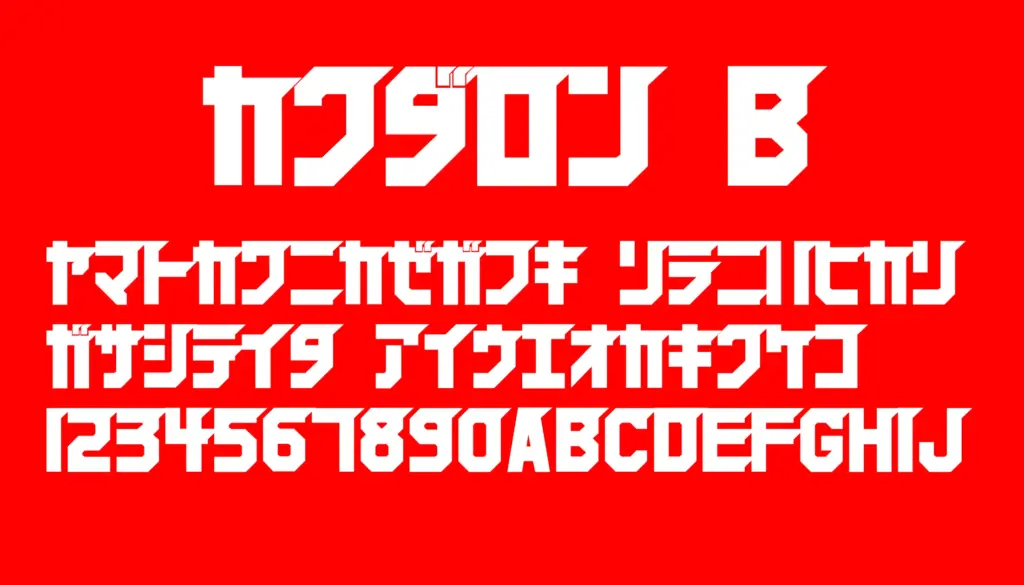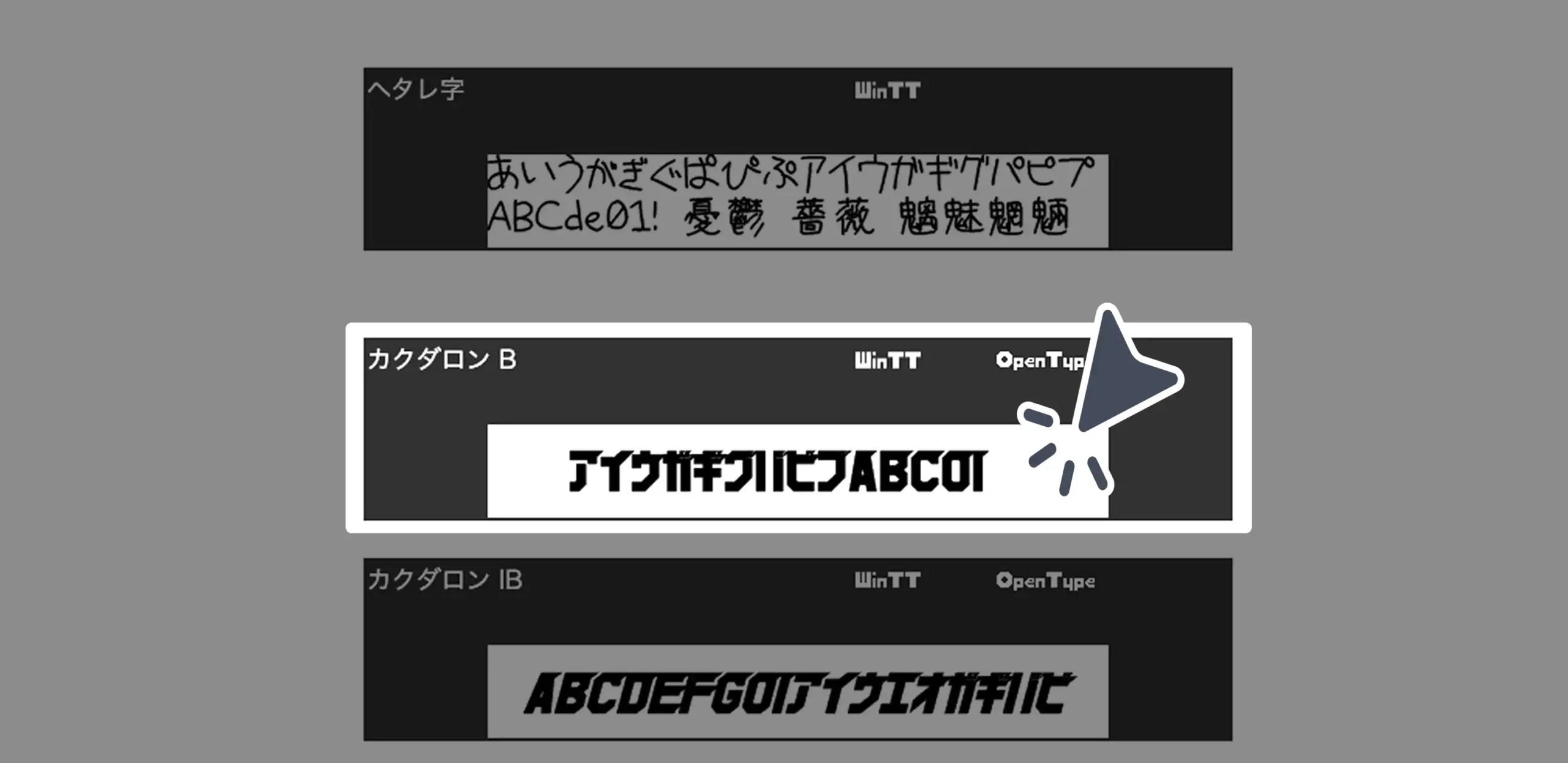
極太で角ばったシルエットが印象的なインパクト重視のフォントです。画面映えするゴツゴツとしたデザインは、タイトルや見出し、アイキャッチに最適。直線的かつ強めのラインで構成されており、力強く無骨な雰囲気を演出できます。ひらがなは非対応ですが、カタカナ+アルファベットで構成されたシーンでは存在感を放ちます。
カクダロン B